本文详细剖析11款字体设计的全过程。设计+解析+动效,以最简单易懂的方式,合成一篇字体设计分享文章,希望你会喜欢,并留言交流。
字体设计对设计师来说应该是蛮重要的技能,甚至可能说是最基本的技能,因为经常用到这项技能,比如标志标准字体、海报、主题活动主画面、线上Banner等等。
做一款字并不难,难在做好一款字。
先讲讲我的做字流程:
确定要做的字
理解和消化字的含义
网上搜寻相关参考资料
边想边画手稿
电脑执行(软件AI)
润色包装
下面案例会重点讲解电脑执行(软件AI)这部分,包括初稿、过程稿、亮点详解、难点剖析等等,还有一些在特点字风格下的做字要点。
在这次的分享中我更多的从设计技法的纬度去剖析,在创意层面则会稍微提一下。
我在设计大部分的常规商业字体时,会严格遵守三条原则,分别是:
中宫外扩
慎用技法
重量一致
1. 中宫外扩
中宫收紧这种情况一般只存在在书法字体中,显得紧凑有力。
中宫外扩一般适用于方方正正的标准美术字,即常规商业字体设计,使用此形式会让字体宽松而且更规整。
因此这两种形式并没有好坏之分,视情况而定。
2. 慎用技法
这里的技法是指字体设计时可以增加字体的设计感形式感的一些技法,比如:连笔断笔、笔画特征点缀。
技法需克制使用,如若泛滥使用,则会使字体降低了美感,甚至丢失了识别度,过犹不及。
比如下图中设计的字体,是什么内容?你是否还看得出来呢?
「感官」二字能看得出来,后面两字是否无法识别,只能连蒙带猜了呢?是的,因为识别性太弱了。字体设计的识别度严重不够,恰恰是因为忽视字体结构造成的。
我个人觉得,美观性和识别度同等重要,好比一双筷子缺一不可。
切记不可一味追求炫技,需克制,把握好技法使用的度。需要更多考虑字体的识别性和美观度。
3. 重量一致
重量一致是指在一款字体设计中,在视觉上每一个字都保持均等的分量,也就是在视觉上感觉每个字都一样重。
举个例子,如下图中的「一二三四国馨」,这些字的笔画从一笔到二十笔递进,疏密各不一致,为了达到视觉上一致的分量,在笔画少的字体中笔画调得相对粗一些,而笔画多的字体则将笔画调得相对细一些,从而达到整体协调。
下面让我们进入具体字体案例的分析中吧。
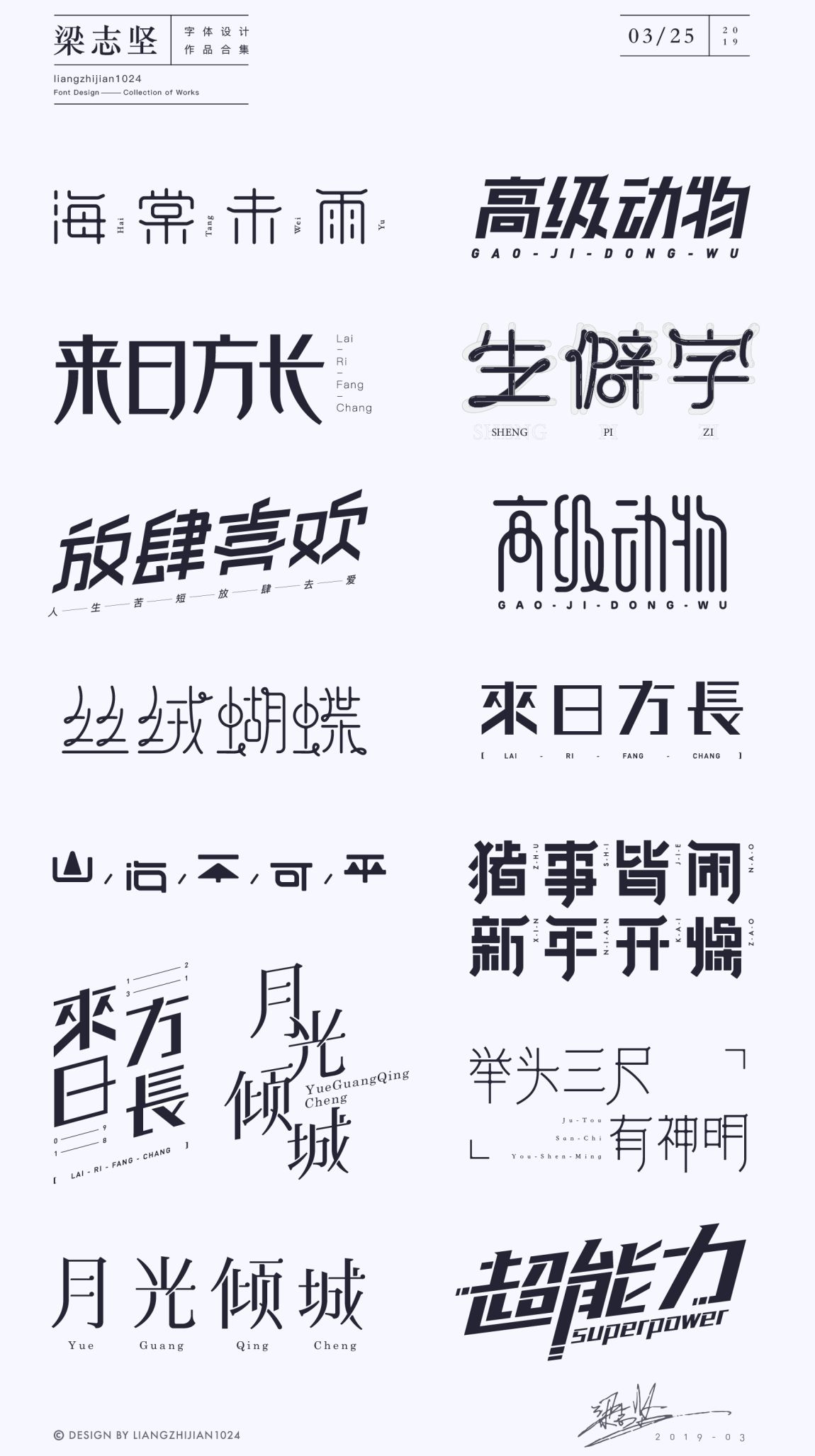
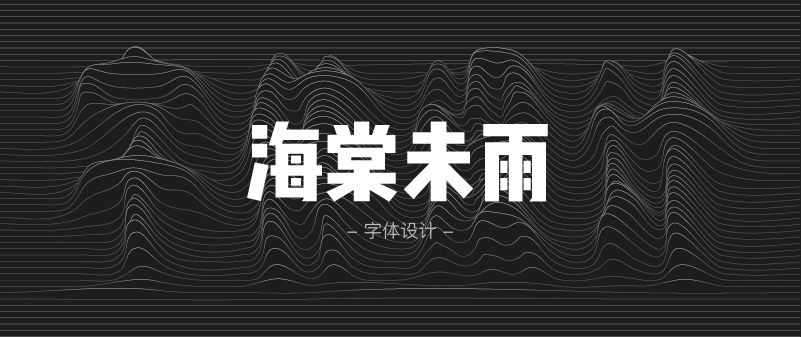
1. 前期思考
当拿到这个主题的时候,我想到的是唯美、古典。定下字体气质,便按这个方向找寻合适的参考。
在搜寻参考的时候我突然想到了古建筑的屋檐,也想到了用海浪的形态,即把四个字做成海水流动的既视感。
最终考虑到古建筑屋檐的特征更有唯美气质,屋檐特征更为抽象简约,可以不繁琐且巧妙镶嵌在字体笔画中,与之共生,因此选了这个创意点。
2. 绘制手稿
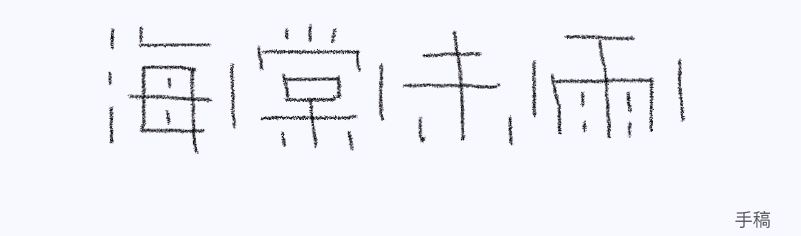
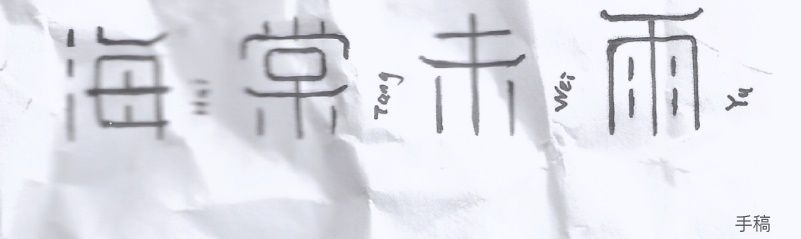
3. 字库字体结构参考
接下来进入电脑执行,首先我会打「海棠未雨」几个字库字体放在一边,便于随时参考字体结构,也能避免自己当局者迷犯低级错误。
4. 雏形
用钢笔工具勾勒出基本型。
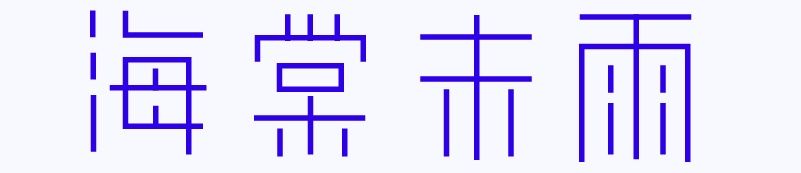
3. 初稿
做字时需不断检查「单个的字」和「整体的字」。
单个的字:主要检查字体内部偏旁部首之间的位置距离是否协调,再就笔画与笔画之间的亲疏关系。
整体的字:主要检查各字体的重量是否一致。
总而言之就是观察字体的「识别性」和「美观度」。
现阶段,感觉「棠」字略宽,「未」字略小,「雨」字高了。
4. 调整
字体细节调整之后舒服了很多,好多方角部分做了「倒圆角」处理,更耐看了。
做到这一步,感觉整款字体已经没有什么大毛病了,但依然平平无奇。
5. 增强字体古典气质
加入了古建筑屋檐的抽象形,融入每一个字的某一笔画之中。添加了字体唯美、古典的气息。然后在笔画交汇处都做了「溢墨」处理(一般书法字才会有墨水溢开的效果),更加深了字体的古韵味道。
6. 一些思考
其实还有好多细节都在设计过程中做了恰到好处的优化。比如:「棠」字上面三笔,中间高两边低,为了识别也为了美观。比如:有古建筑屋檐特征的笔画的位置安放考虑,相邻两字之间的屋檐特征笔画是坚决不能对齐,按这个标准加上因地制宜的调整后,呈现出错落有致富有美感的一幅画面,仿佛远处有一座座高低不同的古建筑,还飘着雨。
7. 做字全流程GIF图
8. 包装
1. 绘制手稿
2. 字库字体结构参考
3. 初稿
快速把基本形执行出来。
字体结构:属于上紧下松。
字体特点:
笔画横细竖粗。
横笔右端倾斜处理。
字体的记忆点在于「来」字的撇和捺,其他字也同样保持这样的特征。
4. 添加字母点缀
5. 优化
「来日方长」四字紧凑排版。点缀字母使用更小字重,为了弱化点缀字母,固在每两行之间添加了横杆,更显精致。
6. 最终稿
最后调整一下细节,比如整体特征笔画的处理,比如「长」字右下角断笔的处理。
7. 做字全流程GIF图
8. 包装
绘制手稿
字库字体结构参考
初稿
该款字体为繁体字,第一和第四个字笔画繁多,第二第三个字笔画略少,因此在设计时候需要特别考虑到「重量一致」的设计原则。
字母点缀
现阶段每个字体的风格还不算非常统一(基本统一,但还不够)。
修改调整
「方」字尝试另一种可能,「方」字为了在风格上与「来」字更统一、呼应,因此修改成下图的方案。「长」字的繁体字右下角做了调整,更加协调了。
横版最终方案
经过再三衡量对比,还是觉得「方」字左下角那一画,一笔下来更有力量感,有具设计感。「长」字保持上图最终方案。
之前「长」字右下角那一笔跟「方」字左下角那一笔严格对称呼应倾斜度,从而忽略了长字的整体协调性和稳重感。做了调整之后协调稳重多了。